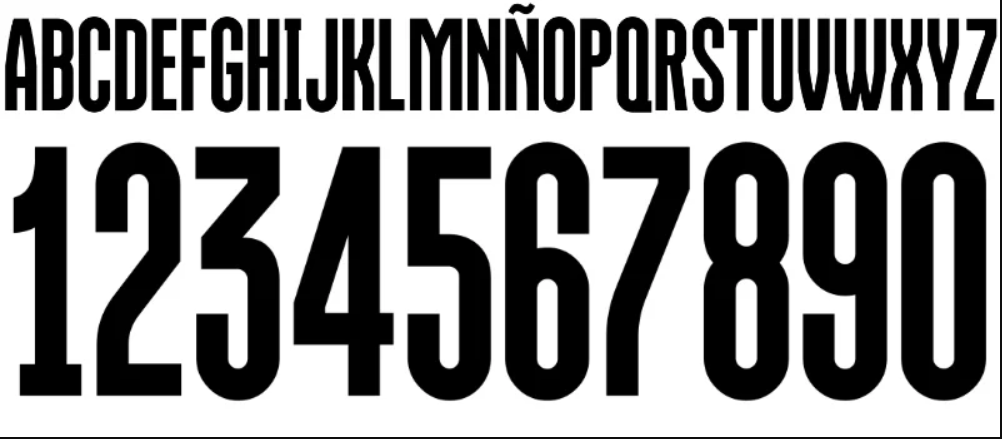
O futebol italiano respira tradição e estilo, e o Modena FC não foge à regra. Para a temporada 2025-2026, os “Canarini” (Canários) entram em campo na Serie B vestindo uniformes produzidos pela New Balance, que caprichou na identidade visual.
Neste post, trazemos a tipografia exclusiva utilizada no icônico uniforme Gialloblù (amarelo e azul), permitindo que você crie personalizações fiéis e designs inspirados no Calcio.
- Conteúdo: Jogo completo de números e letras (alfabeto maiúsculo) conforme usado pelos jogadores.
Estilo Visual e Aplicação
A New Balance desenvolveu para o Modena FC uma fonte que mistura o clássico com o contemporâneo. A tipografia apresenta um peso médio a robusto (Bold), ideal para visualização rápida nas costas da camisa.
Os números possuem cortes geométricos sutis e uma estrutura sólida, transmitindo estabilidade e força. É um estilo visual que harmoniza perfeitamente tanto com a camisa titular amarela quanto com o kit reserva, mantendo a elegância típica dos clubes da região da Emilia-Romagna. É indispensável para quem deseja reproduzir o uniforme oficial ou criar mockups de alta fidelidade.